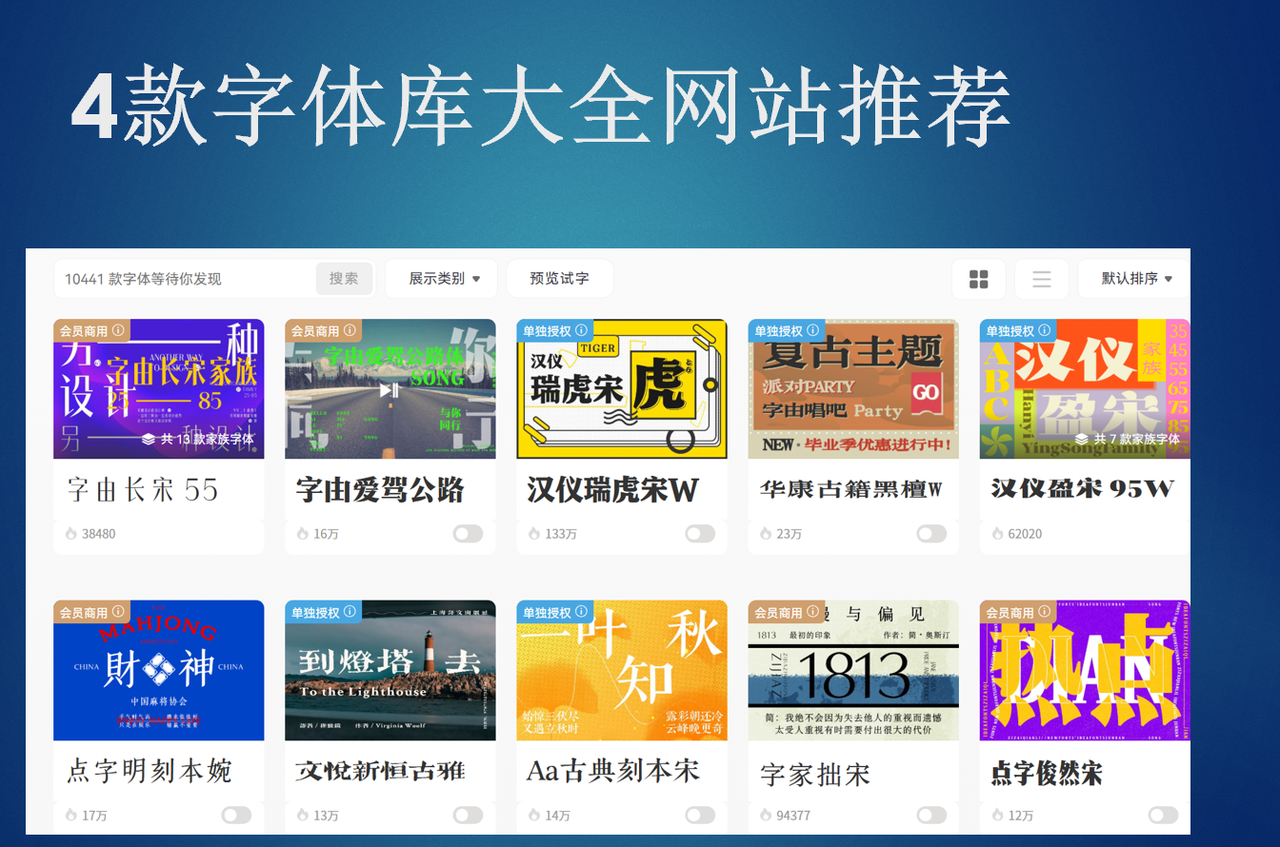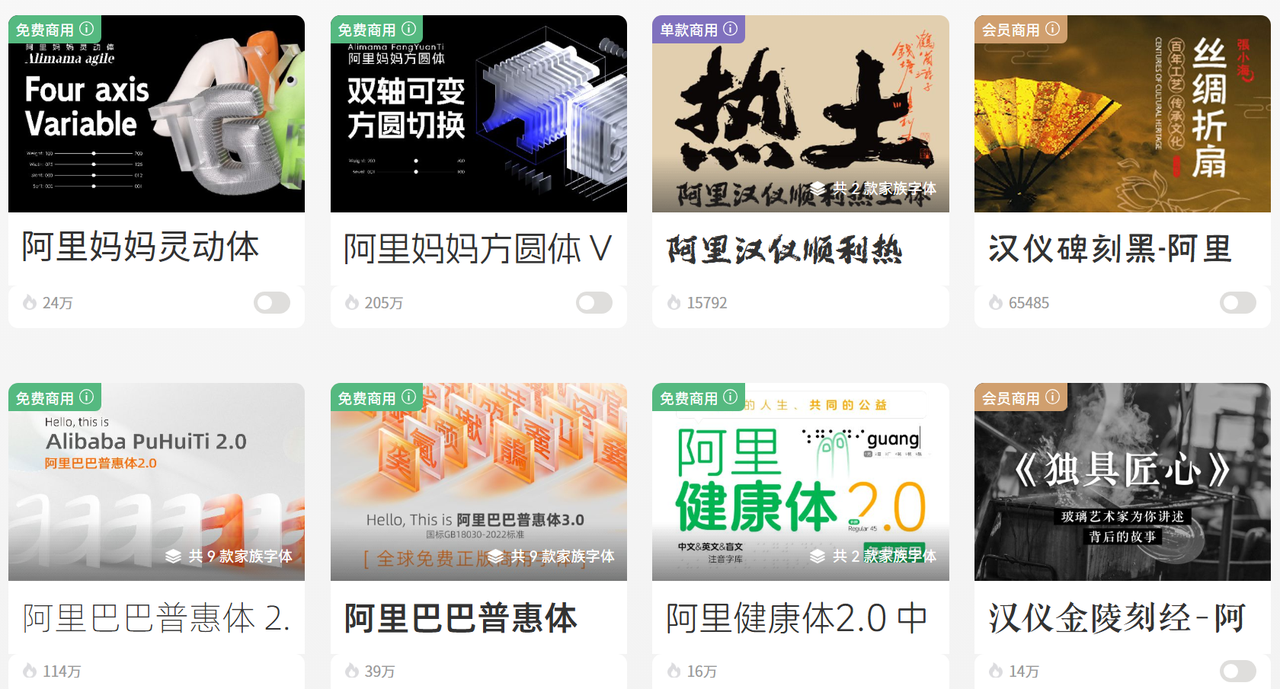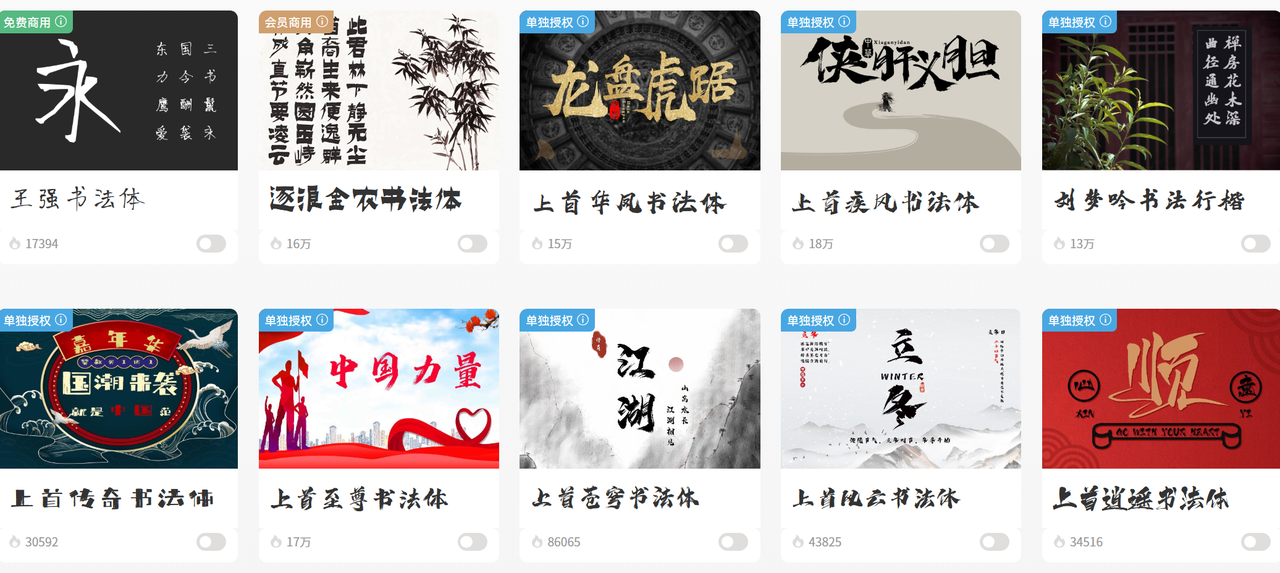
2026 必收藏!4款字体库大全网站推荐
如今设计创作的需求不断升级,从日常办公排版到创意海报设计,从品牌 LOGO 打造到自媒体内容创作,处处都需要合适的字体来加持质感。我也曾常为找字体发愁,翻遍各类平台却难寻心仪款,还总担心版权问题。现在字体需求越来越细分,从常规办公到创意设计,从个人使用到商业授权,一款好用的字体库网站能直接节省80%的找字时间。本文就给大家介绍4个一站式的字体库大全网站,轻松解决你的字体需求。
字由网
我平时使用最多的就是字由网,字由网的优势的很突出,首先是字体资源够全够优质,收录了5000+款字体,其中1000+款是厂商公开授权的免费商用字体,还有500+款品质正版字体可商用授权,涵盖宋体、黑体、书法体、创意体、特效体等所有风格,无论是日常办公用的简约黑体,还是海报设计用的毛笔书法体,或是电商设计用的活泼特效体,甚至是品牌出海需要的多语种字体,在这里都能找到。更贴心的是,每款字体的详情页都会明确标注版权方和授权范围,有源可查,再也不用怕误用字体导致侵权,客户或平台要版权证明时也能直接导出,省去很多麻烦。
先说说我日常高频使用的基础字体,阿里系字体适配性很强,覆盖办公、排版等多种基础场景。无论是Word文档排版、PPT制作,还是自媒体正文编辑,用它都不会出错,自带专业感。
书法体也是字由网的热门品类,涵盖楷书、行书、草书、隶书等多种类型,适配海报、牌匾、节日物料等场景。比如免费商用的毛笔草书字体,自带笔墨韵味,做活动海报、短视频封面标题,让设计更有灵气,字由网还专门整理了毛笔草书字体的应用案例,方便大家参考选用。
除此之外,字由网还有400+款字体特效,尤其是近期上新的款式,贴合当下热门设计风格,可自定义内容并导出使用,不用额外用设计软件调整,省时又省力。
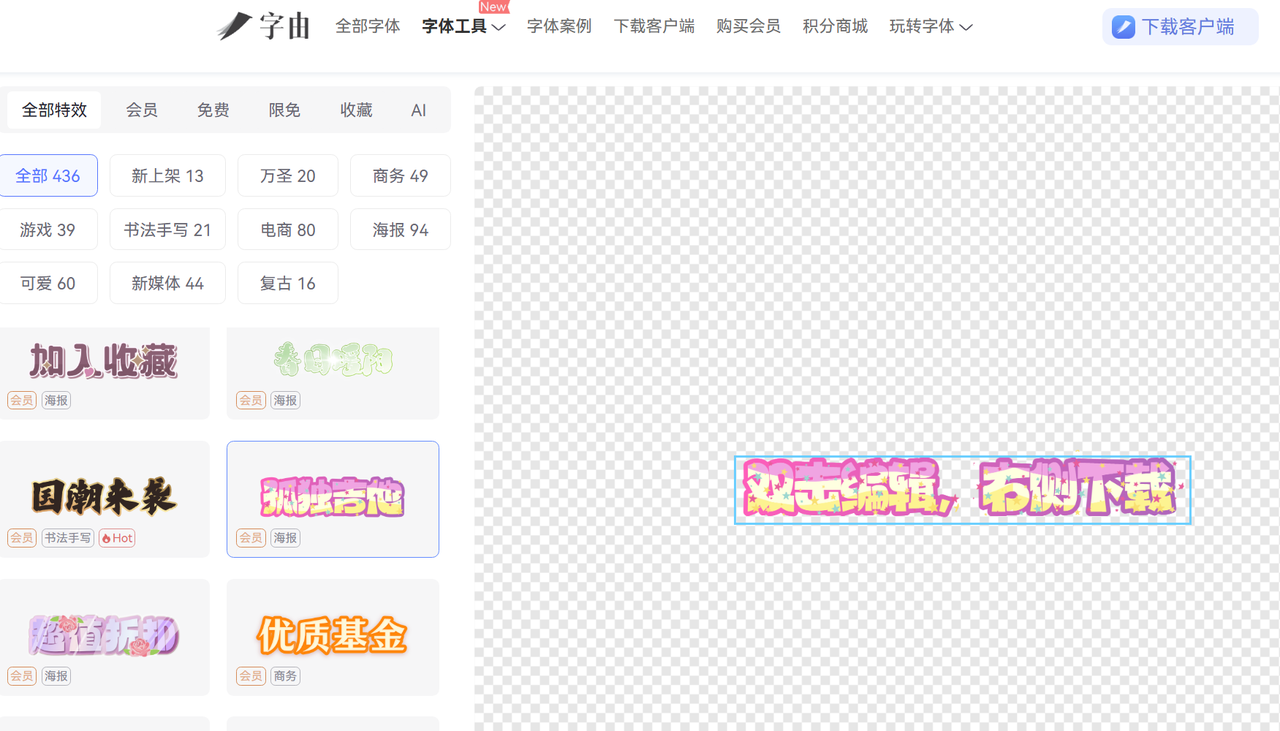
猫啃网
目前猫啃网已有近千款优质中文免费商用字体,更新频率很高,经常能找到新款小众字体,它的字体更聚焦中文场景,无论是楷书、行书、草书等传统书法体,还是简约无衬线体、可爱卡通体、复古印刷体等创意字体,都能满足日常个人使用和小型商业设计需求。网站的分类也很清晰,按字体风格、使用场景、字体作者进行细分,比如想找适合手写笔记的字体,直接点击“手写体”分类就能筛选,不用在海量字体中盲目翻找。
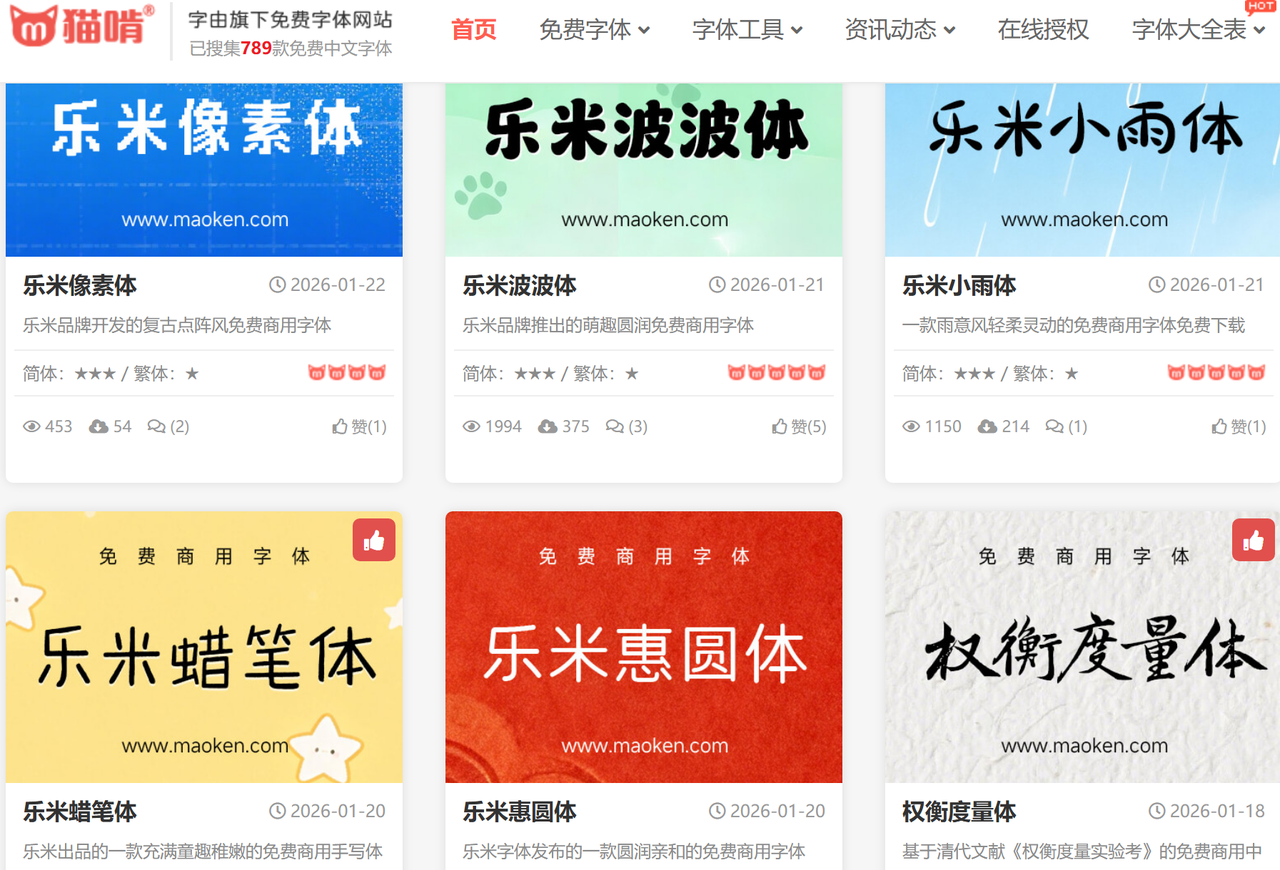
100font
100font也是一款我用着性价比不错的字体网站,100font收录了600+款多语种字体,除了中文字体,还有英文、日文、韩文等多种语言的字体,适合跨境自媒体、外贸企业、多语种海报设计等场景,所有字体均经过严格版权核验,确保免费商用,不用担心侵权问题。字体风格涵盖日常通用款和创意款,无论是办公排版、海报设计,还是跨境宣传物料排版,都能找到适配的字体。
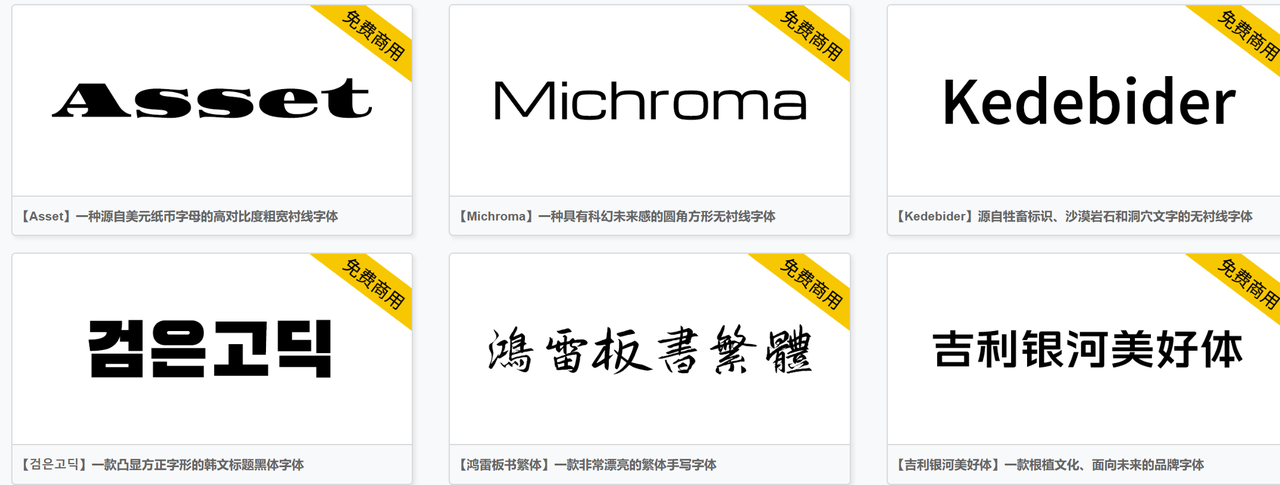
站酷字库
最后一款是站酷字库,虽然站酷字库的字体数量不如字由网多,但每一款都是精心筛选的原创字体,比如站酷庆科黄油体、站酷文艺体、站酷酷圆等热门字体,风格独特,辨识度高。这些原创字体打破了传统字体的刻板印象,既有复古质感,又有现代设计感,能让你的设计作品脱颖而出。网站界面和站酷社区一脉相承,简约有设计感,浏览字体的过程就像看设计作品,既能找字体,又能获取创作灵感,一举两得。